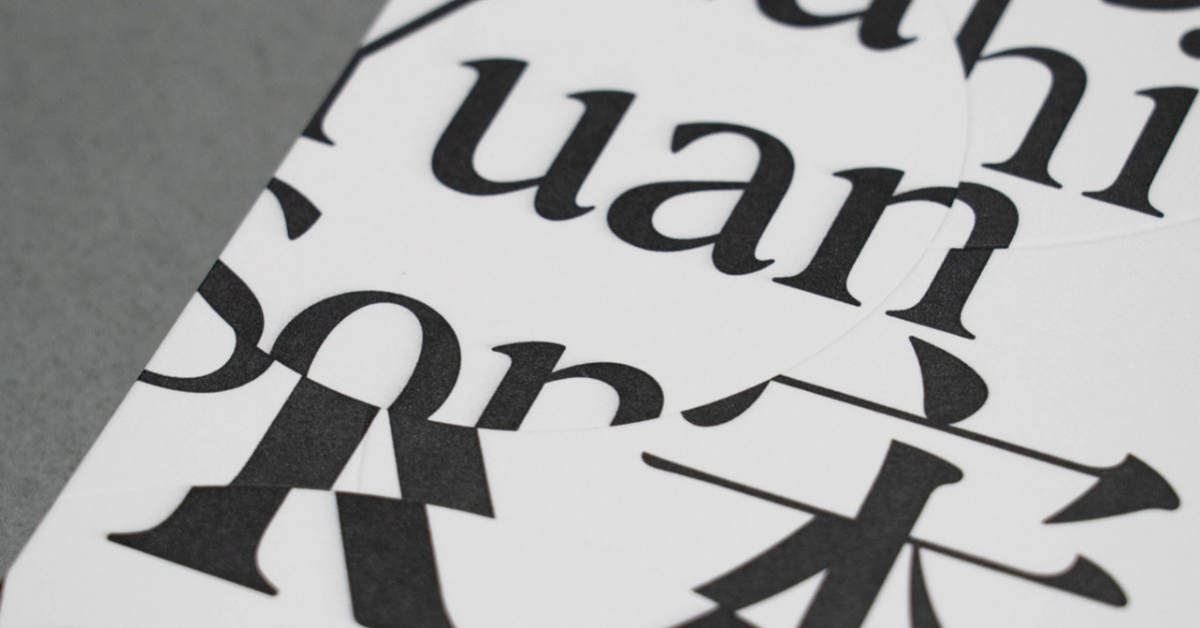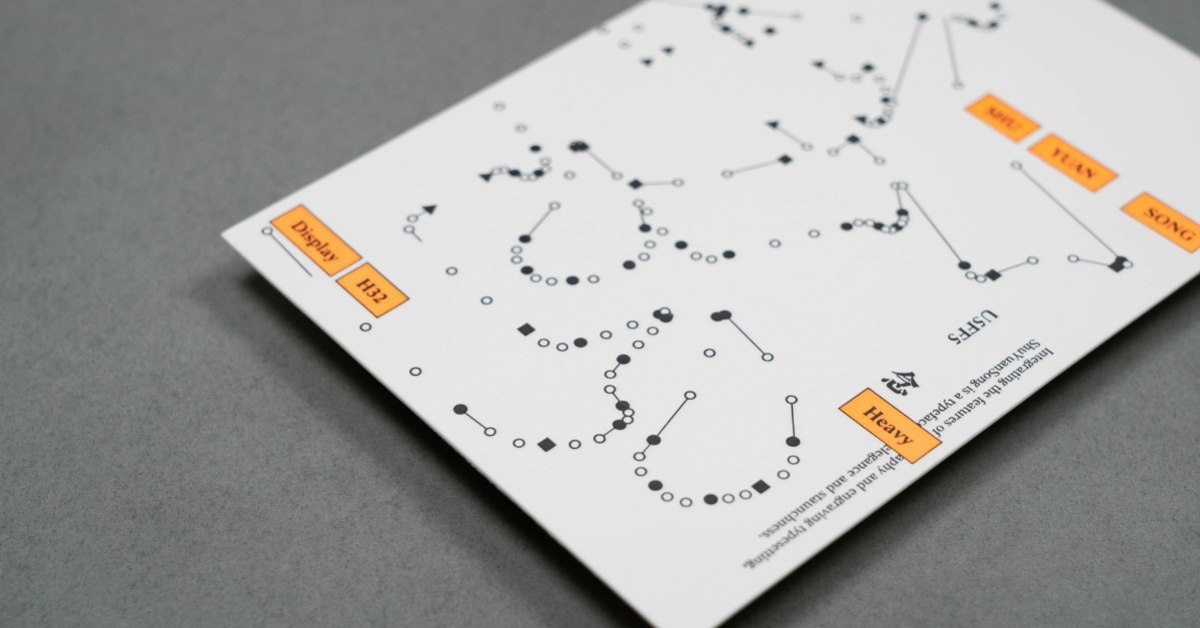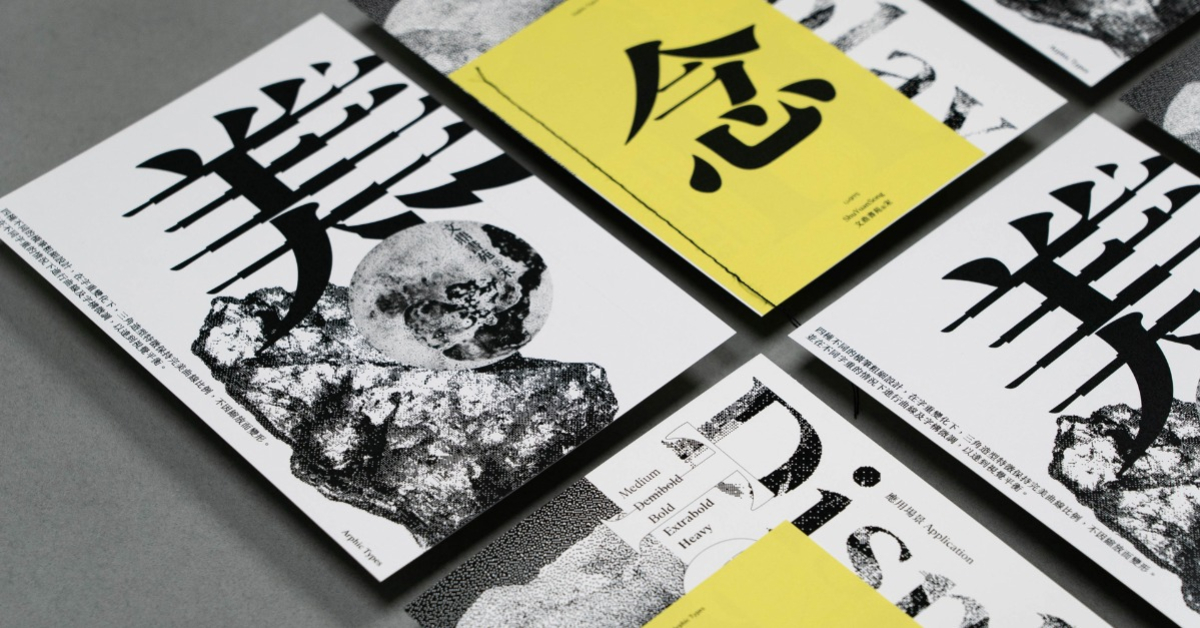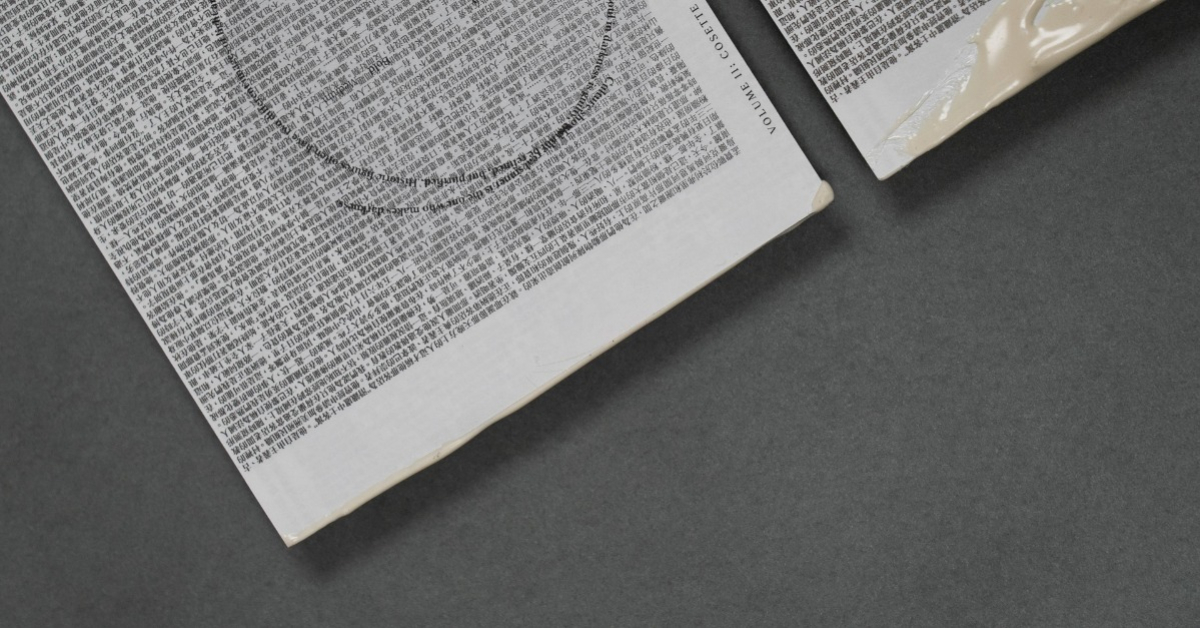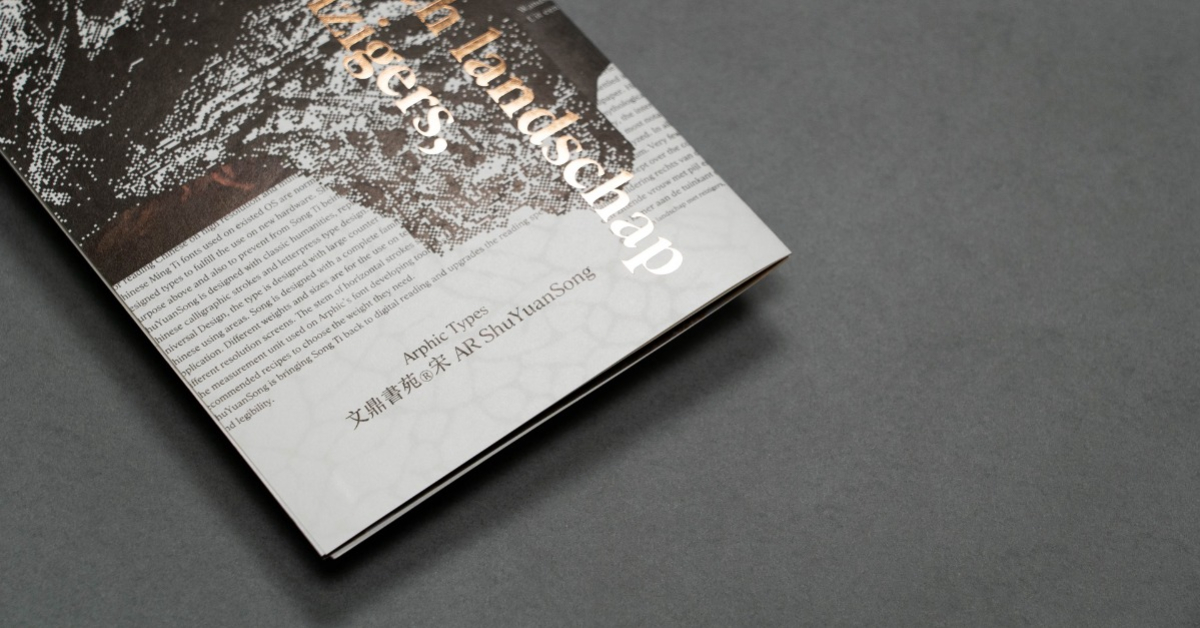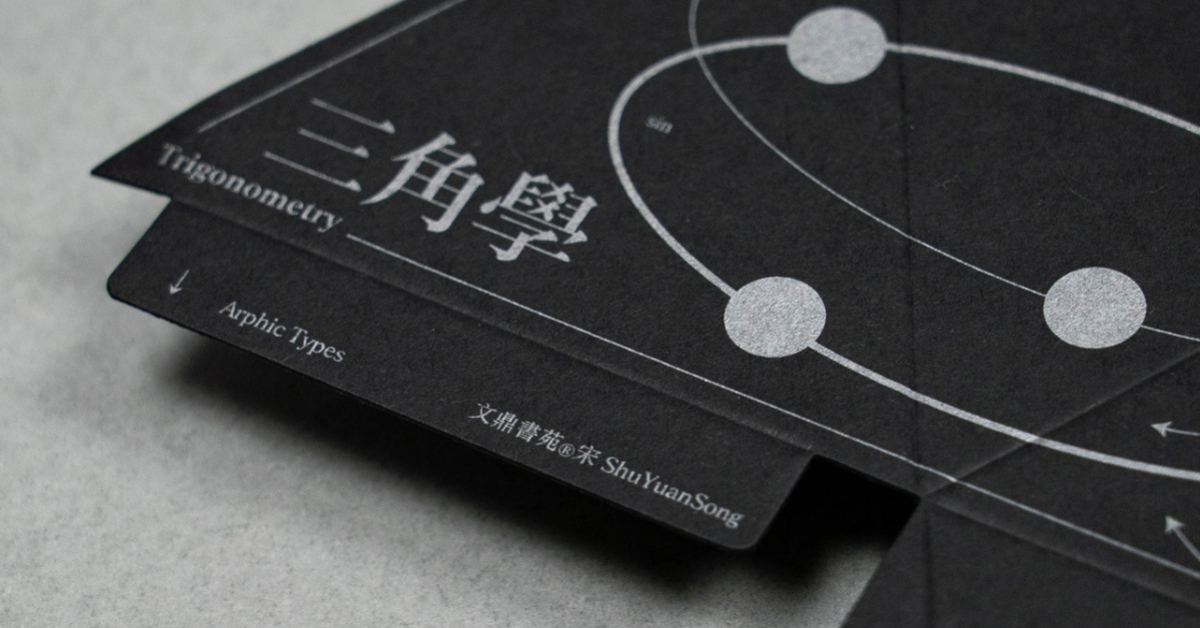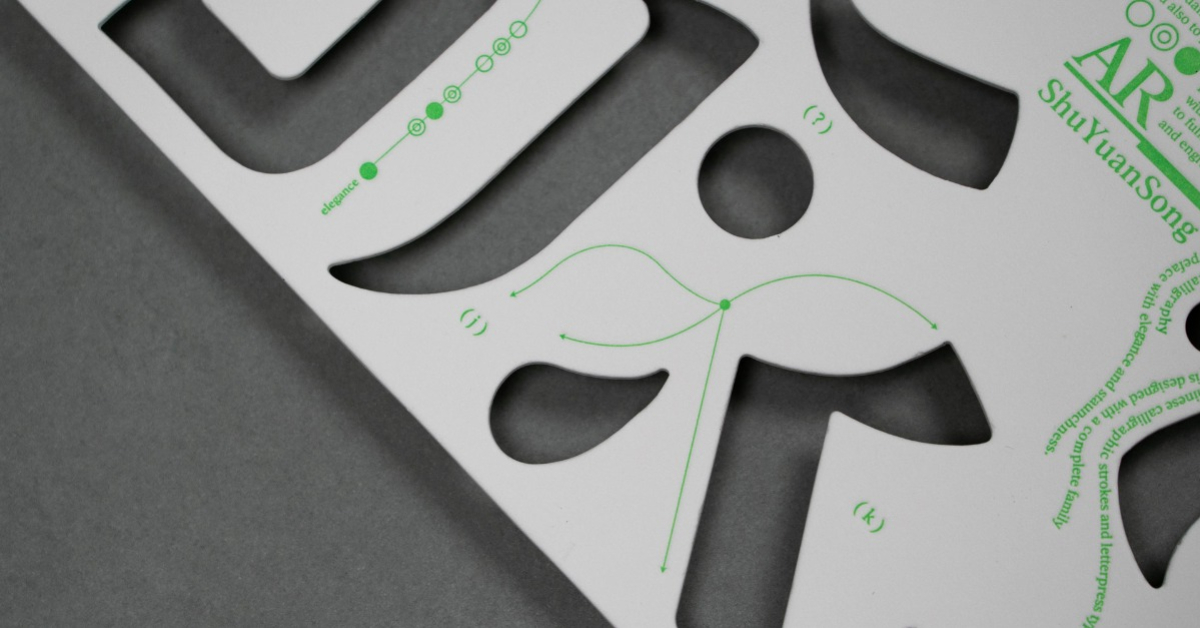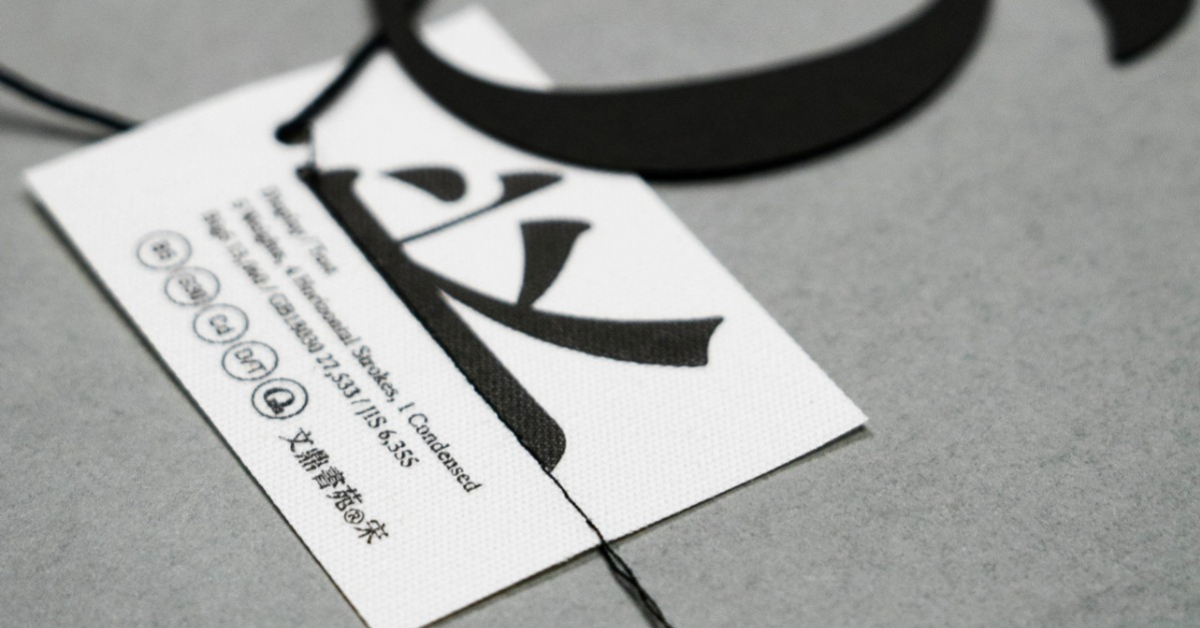
因應中文電子閱讀趨勢與高解析度、多螢並存需求,加上現有OS系統內明/宋體橫筆普遍偏細,必須有新設計來滿足新硬體發展的需求。
「書苑宋」設計是挽救高閱讀性的宋體字逐漸被黑體字型取代的危機。
採古典人文風格,改變機械般直線的宋體造型,融合楷書書法筆韻、活版印刷字模刻工元素與流線型曲線的創新造型。
並結合Universal Design的設計精神,採大字腔結構,整合泛漢字地區的眼球閱讀習性而設計。
文
圓潤的三角點。
筆尾裝飾角以二側的弧線,柔化頂端尖角,呈現書法的筆韻。
與撇筆筆尾造型呼應。
撇筆筆尾採圓弧設計。
起筆融合刀刻的 " 尖 " 與墨暈的 " 圓 "。
情
左 : 尖微外擴;右 : 小圓
融合橫筆尾三角及豎筆小圓造型元素。
勾筆的下方轉折與尾端收筆皆為圓弧。
左 " 尖 ";右斜圓弧二側微外擴。
取漢字筆畫元素特徵,融入西文字體設計。
「書苑宋」完整字體家族提供全方位應用。
從內文到標題編輯所需要的字重,以及因應各種不同解析度,不同使用Sizes的多螢顯示。
「書苑宋」從橫筆粗度16到粗度62(EM=1000)的字型家族,使用者可依據使用配方建議,選取適當字型使用。
5 Weights
4 Horizontal Strokes
1 Condensed
四種不同的橫筆粗細設計,在字重變化下,
三角造型特徵保持完美曲線比例,不因縮放而變形。
並在不同字重的情況下進行曲線及字構微調,以達到視覺平衡。
文鼎書苑宋字體使用成果
2022年以文鼎書苑宋為題,邀請仰角視覺整合設計文鼎書苑宋套卡。現已贈送完畢。
在發想初衷時,便以「平面設計」的角度來出發,希望可以跳脫出過去以往常見的「機能」、「功能說明」、甚至是「工具書」等導向的印刷品,反而是透過視覺上的呈現才是最直覺的,因此,不去更改筆畫造型或是做壓縮扭曲之類的處理,這些應該留給設計師或是字體使用者的來作發想與延伸,
為了完整鞏固這個目標,我們也搭配了不同的印刷方式(平板、數位、凸板)以及後加工處理,都是為了讓設計師或者使用者能夠更容易想像出的使用的情境,冀望能在這份印刷品上預覽未來應用的各種可能性。